Почерк Эйнштейна превратят в шрифт
Если денег хватит
Специалист по типографике Харальд Гайслер решил создать серию шрифтов, которые повторяли бы почерк известных личностей. С 2009 года он ищет рукописи, сканируя буквы и превращая их в электронные. Работа настолько кропотливая, что каждую литеру одной личности приходится переделывать по нескольку раз, так как они все отличаются друг от друга.
Чуть больше месяца назад он запустил проект на Kickstarter по сбору средств для создания шрифтов, основанных на почерках всемирно известных личностей.
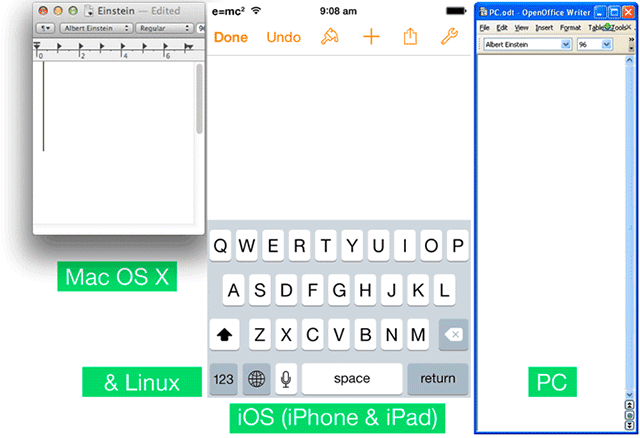
Такое большое дело Харальд Гайслер оценивает в 15 долларов — столько будет стоить базовый набор шрифтов. Цена небольшая, только вот для запуска проекта типографу нужно 15 000 долларов. Проект уже поддержали многие: на данный момент собрано чуть больше 11 000.